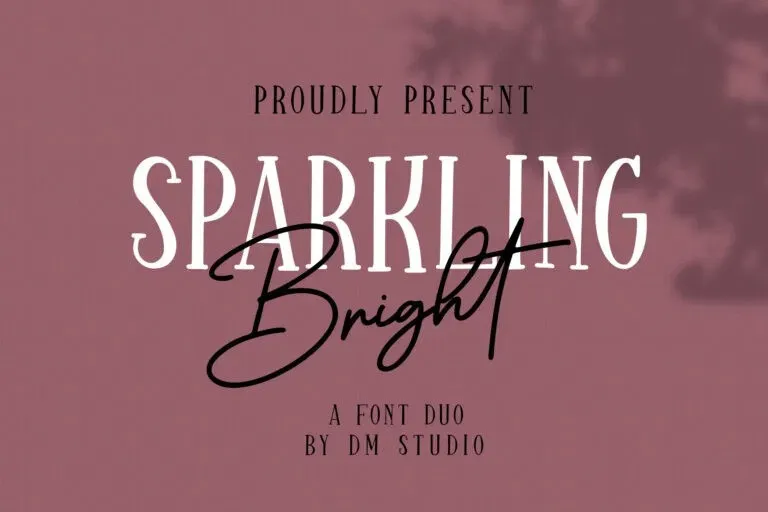
Sparkling Bright Font – Fonte Grátis
Sparkling Bright Font
A fonte Sparkling Bright é ideal para quem procura uma opção vibrante e versátil para projetos criativos. Com seu duo de design único e incríveis alternativas e ligaturas, você pode criar designs inovadores para um leque amplo de aplicabilidades. Perfeita tanto para desenhos a mão quanto para tipografias serifadas ou script, essa fonte tem tudo o que você precisa para transformar suas ideias em realidade. Seja para cartões de cumprimentos, camisetas promocionais ou até mesmo produtos customizados, Sparkling Bright oferece um toque único e atrativo. Suas linhas luminosas e expressivas permitirão que você faça design distintivo para diversos tipos de mercados. Seja em uma festa festiva, uma promoção especial ou um produto personalizado, essa fonte terá a sua identidade marcando o campo. Experimente já Sparkling Bright e comunique-se com vigor através do seu design.